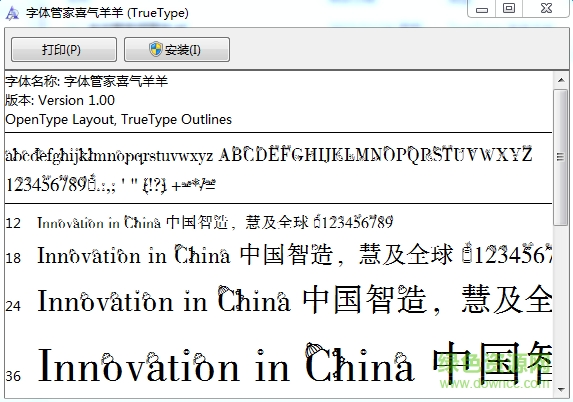
軟件介紹 軟件標(biāo)簽: 字體管家喜氣羊羊 字體 字體管家喜氣羊羊體是一款很有特色的電腦字體,寫出來的字體上海帶有精美的裝飾,不像普通字體那樣單調(diào),寫出來的字很好看,喜歡的朋友可以來綠色資源網(wǎng)下載。安裝說明:1.在綠色資源網(wǎng)下載字體包,并解壓縮2.最簡單的安裝方法:雙擊字體文件,點擊安裝按鈕即可2.批量安裝方法:將字體文件放到C:\Windows\Fonts溫馨提示:本站所有字體資源僅供個人學(xué)習(xí)與參考,如需商業(yè)使用請到相關(guān)官網(wǎng)授權(quán) 軟件截圖 上一張下一張(1 / 1) 安裝詳細(xì)截圖 猜你喜歡 字體管家 手機字體 字體管家 字體管家是一款擁有不同風(fēng)格的書法字體,包含上萬款中文、贏完、藏文等字體模板,綠色資源網(wǎng)收錄了最全的字體管家字體,歡迎大家免費下載使用,商務(wù)使用請到官網(wǎng)授權(quán)! 查看更多>> 字體管家青蔥字體 4.82M/中文/10.0/下載 字體管家細(xì)黑體 2.35M/中文/0.0/下載 字體管家扁黑體 6.95M/中文/10.0/ttf版下載 字體管家黑體 10.46M/中文/10.0/ttf版下載 字體管家仿宋體 11.88M/中文/10.0/下載 字體管家小南瓜 2.70M/中文/9.2/下載 手機字體 手機字體是智能手機常用的字體。每款手機都有自己默認(rèn)的字體,如果你不喜歡,可以更換成自己喜歡的字體類型,這個時候就需要下載對應(yīng)的手機字體了,有需要的朋友,趕快下載體驗吧! 查看更多>> 牽?;ɡ@青藤體 7.05M/中文/10.0/下載 伯樂丫丫體手機字體 2.02M/中文/10.0/v1.0 安卓版下載 伯樂花香體 2.06M/中文/10.0/下載 暖色君小威體字體 7.70M/中文/10.0/下載 字體管家喜氣羊羊 8.85M/中文/10.0/下載 字體管家喬喬體 3.14M/中文/10.0/下載 其他版本下載 標(biāo)題 大小 更新日期 下載 下載地址 電腦版 字體管家喜氣羊羊 點擊報錯 軟件無法下載或下載后無法使用,請點擊報錯,謝謝! 關(guān)閉報錯反饋 請描述您所遇到的錯誤,我們將盡快予以修正,謝謝! *必填項,請輸入內(nèi)容 本類最新 dreamweaver字體庫 首爾南山體字體 v1.06 官方版 潮字社風(fēng)云簡ttf 潮字社凌渡鯤鵬簡體字體 潮字社曾玉波手書簡字體 微博慧心字體 相關(guān)文章 Photoshop字體安裝使用方法和技巧 如何解決“無法新增字體”問題 Win 7系統(tǒng)安裝字體方法 網(wǎng)頁字體大小設(shè)置方法 怎么改網(wǎng)頁字體大小 在Linux系統(tǒng)中安裝字體的幾種方法 windows7字體顯示問題:打開某些程序的時候顯示的是亂碼 用戶評論 熱門評論 最新評論 發(fā)表評論 查看所有評論(0) 昵稱: 請不要評論無意義或臟話,我們所有評論會有人工審核. 字?jǐn)?shù): 0/500 (您的評論需要經(jīng)過審核才能顯示)